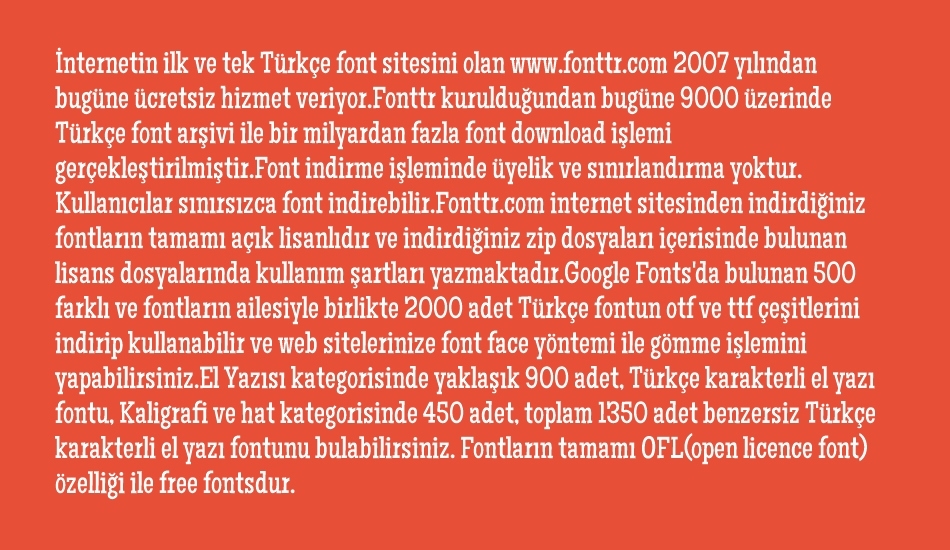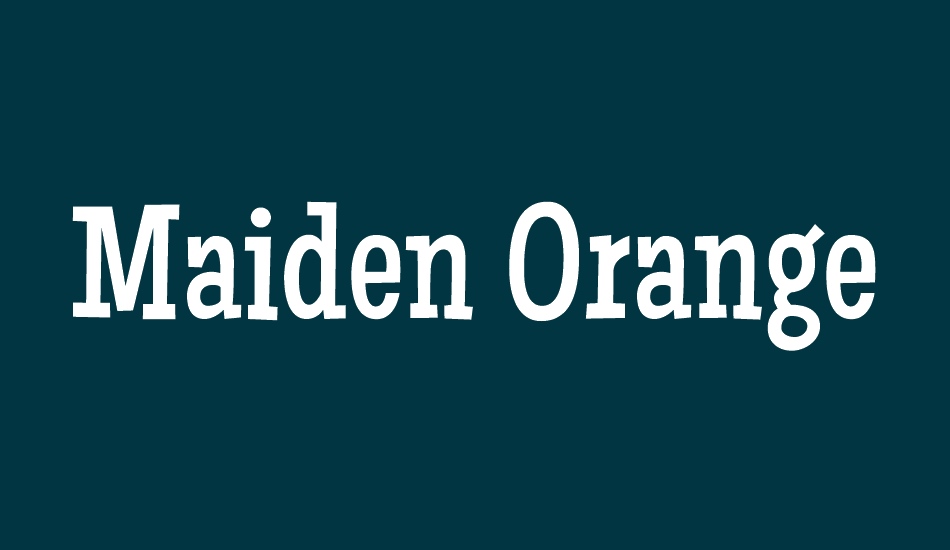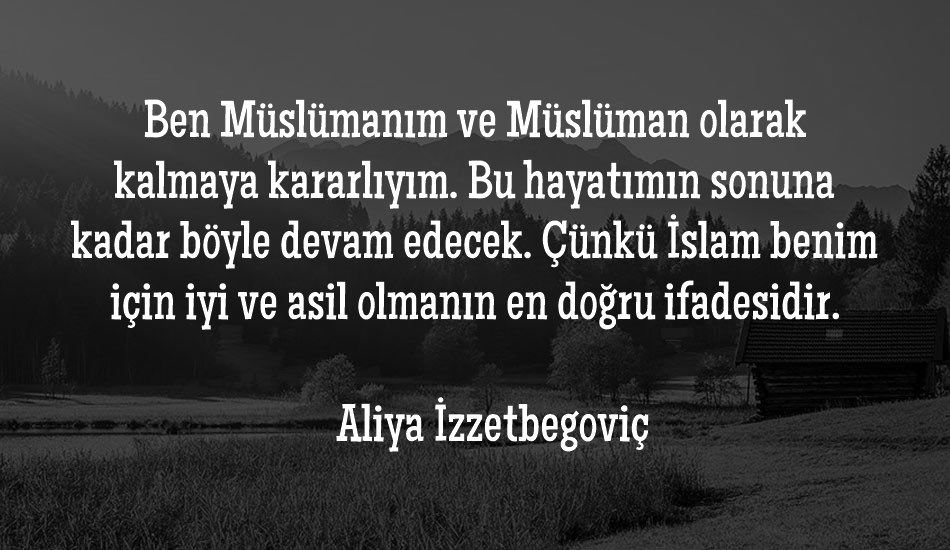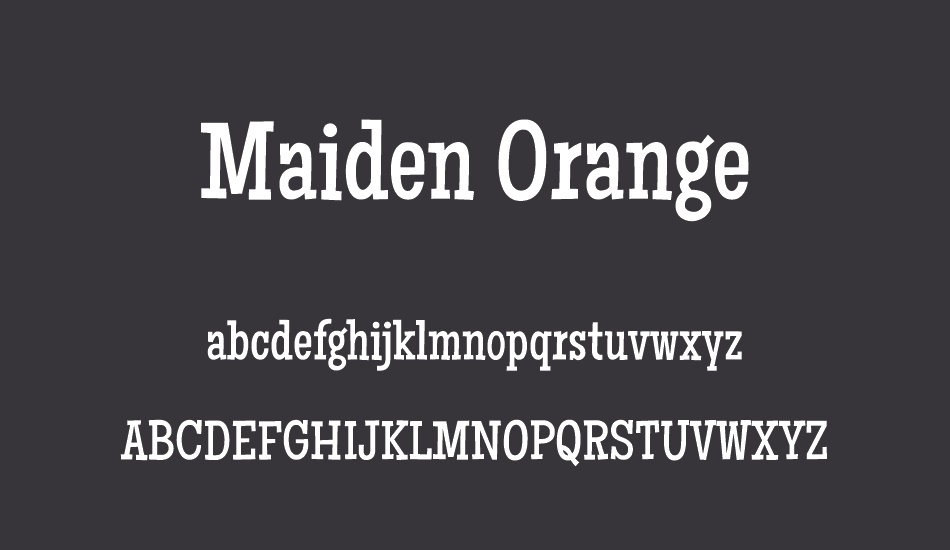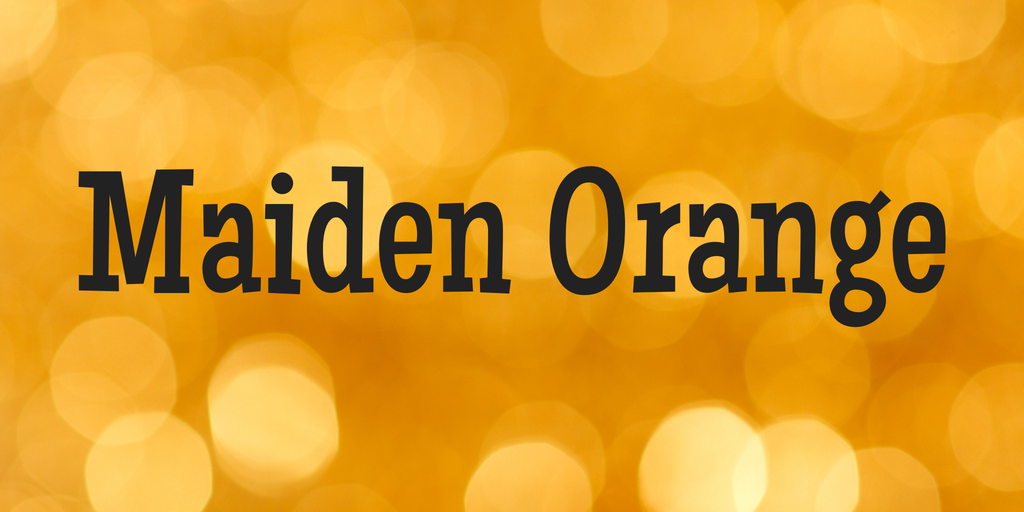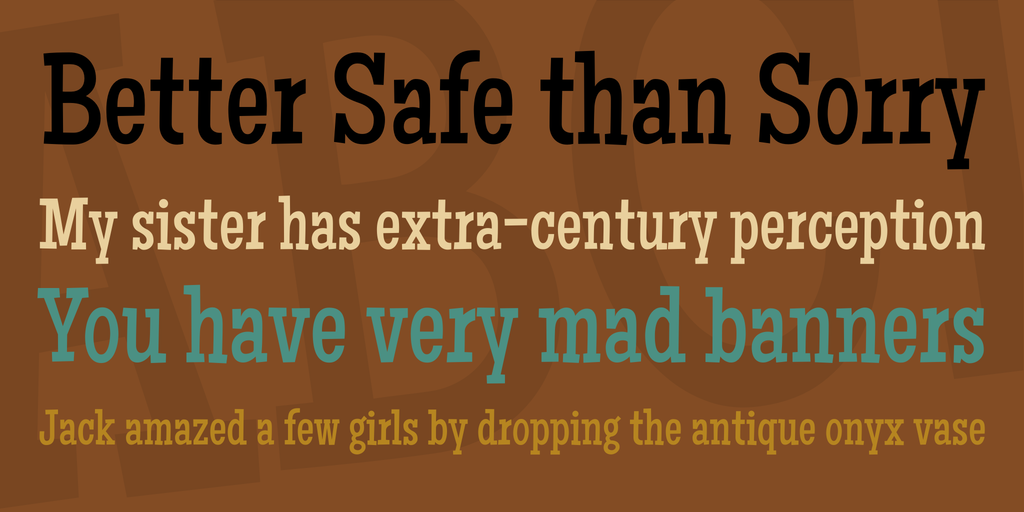
Maiden Orange Font font
Maiden Orange, 1950'lerin özel el yazmalarından ilham alan hafif ve şenlik slab serif yazı tipi. Temiz ve okunaklı, aynı zamanda sıradışı ve güler yüzlü olmasına rağmen, bu yazı tipi çok çeşitli kullanım alanlarına da sahiptir. Çocuk hikayelerinden ilham kaynağına kadar, Maiden Orange'u bir dönüş için al.